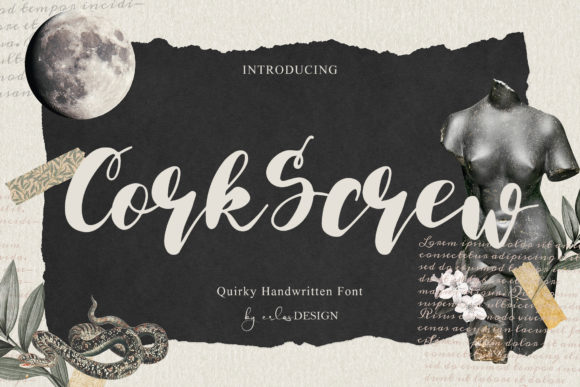
CorkScrew
์ •๋ฐ€ํ•˜๊ฒŒ ์ œ์ž‘๋œ CorkScrew๋Š” ๊น”๋”ํ•œ ๋ฒกํ„ฐ, ๋ถ€๋“œ๋Ÿฌ์šด ํƒ€์ดํฌ๊ทธ๋ž˜ํ”ผ ๋ฐ ์•ˆ์‹ฌํ•  ์ˆ˜ ์žˆ๋Š” ์ƒ์—…์šฉ ๋ผ์ด์„ ์Šค๋ฅผ ์ œ๊ณตํ•ฉ๋‹ˆ๋‹ค.
POD(์ฃผ๋ฌธํ˜• ์ธ์‡„) ์ œํ’ˆ, ๊ฒฐํ˜ผ์‹ ์ดˆ๋Œ€์žฅ ๋˜๋Š” ์†Œ์…œ ๋ฏธ๋””์–ด ๊ทธ๋ž˜ํ”ฝ์„ ๋งŒ๋“ค ๋•Œ CorkScrew๋Š” ์ด์ƒ์ ์ธ ์„ ํƒ์ž…๋‹ˆ๋‹ค.